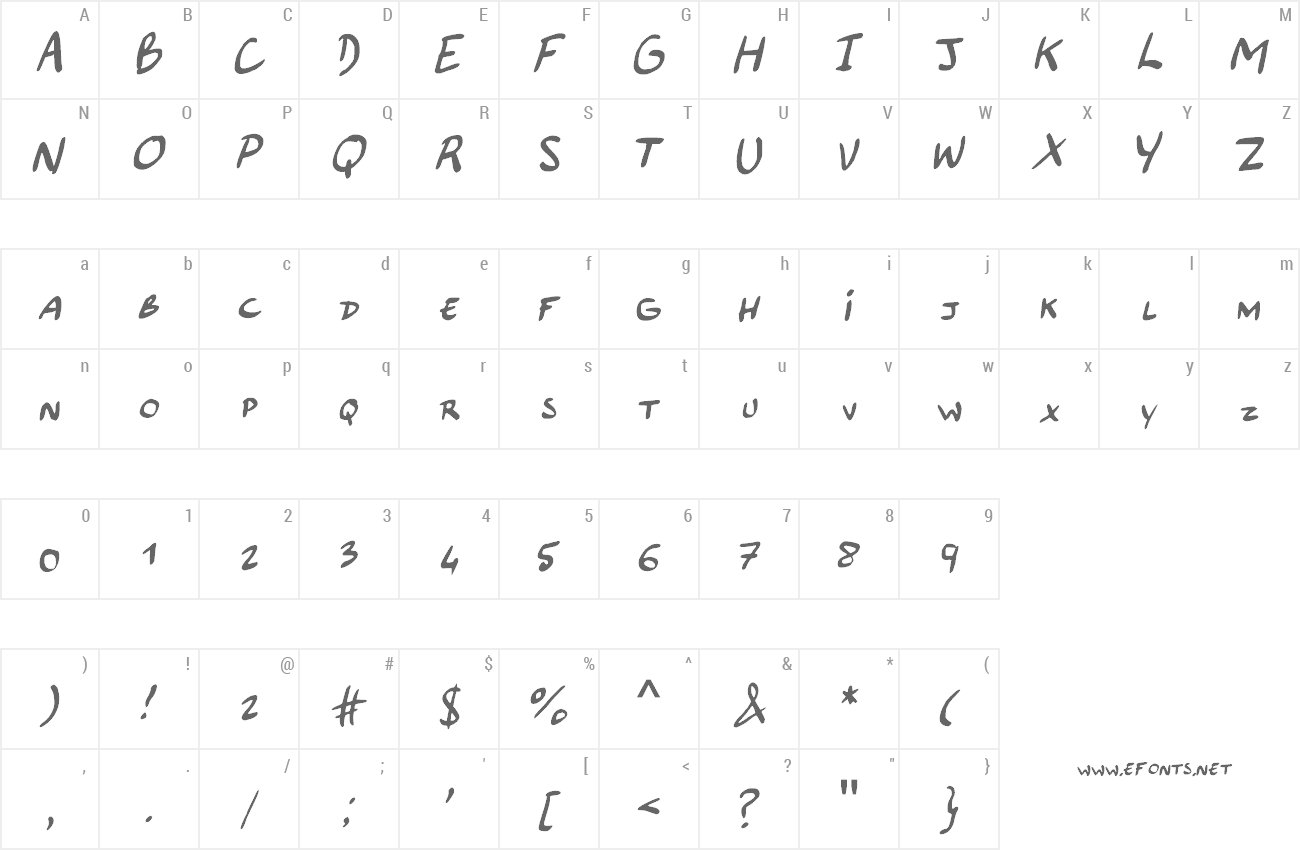
Preview and download Majuscules BD Font. Created by Saskia in Fancy Comic styles with Free for personal use license.
| Font name: | Majuscules BD |
| Author: | Saskia |
| Note by Saskia | |
| Police crée par mes soins grâce photoshop et un créateur de police. Peut servir pour la BD, les comics. |